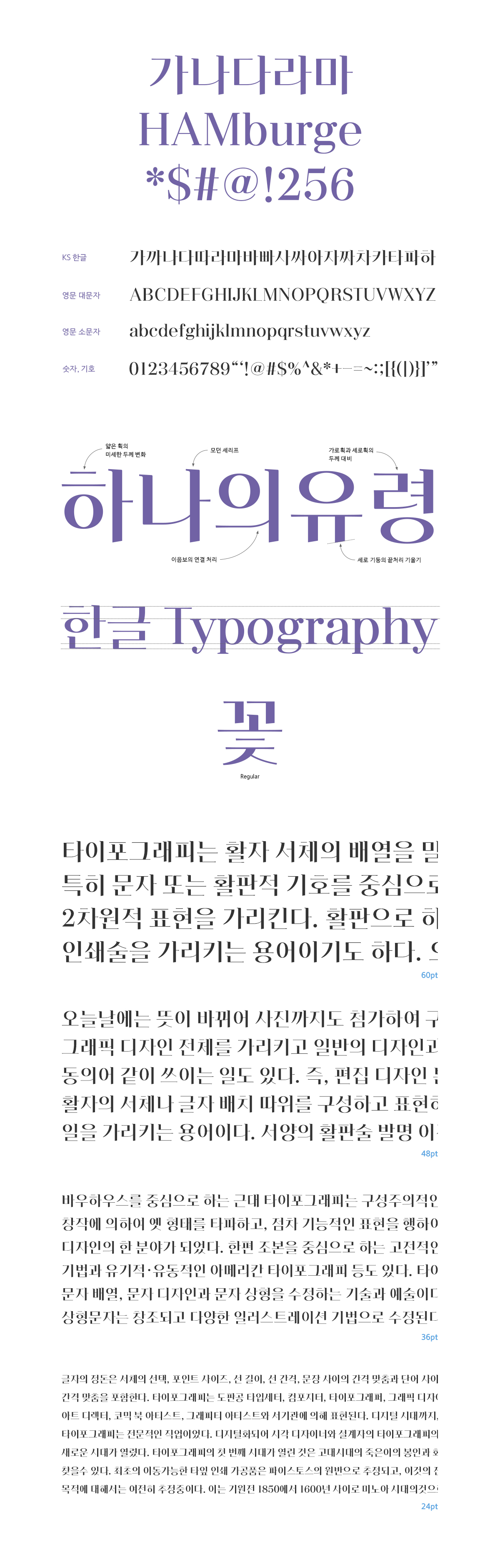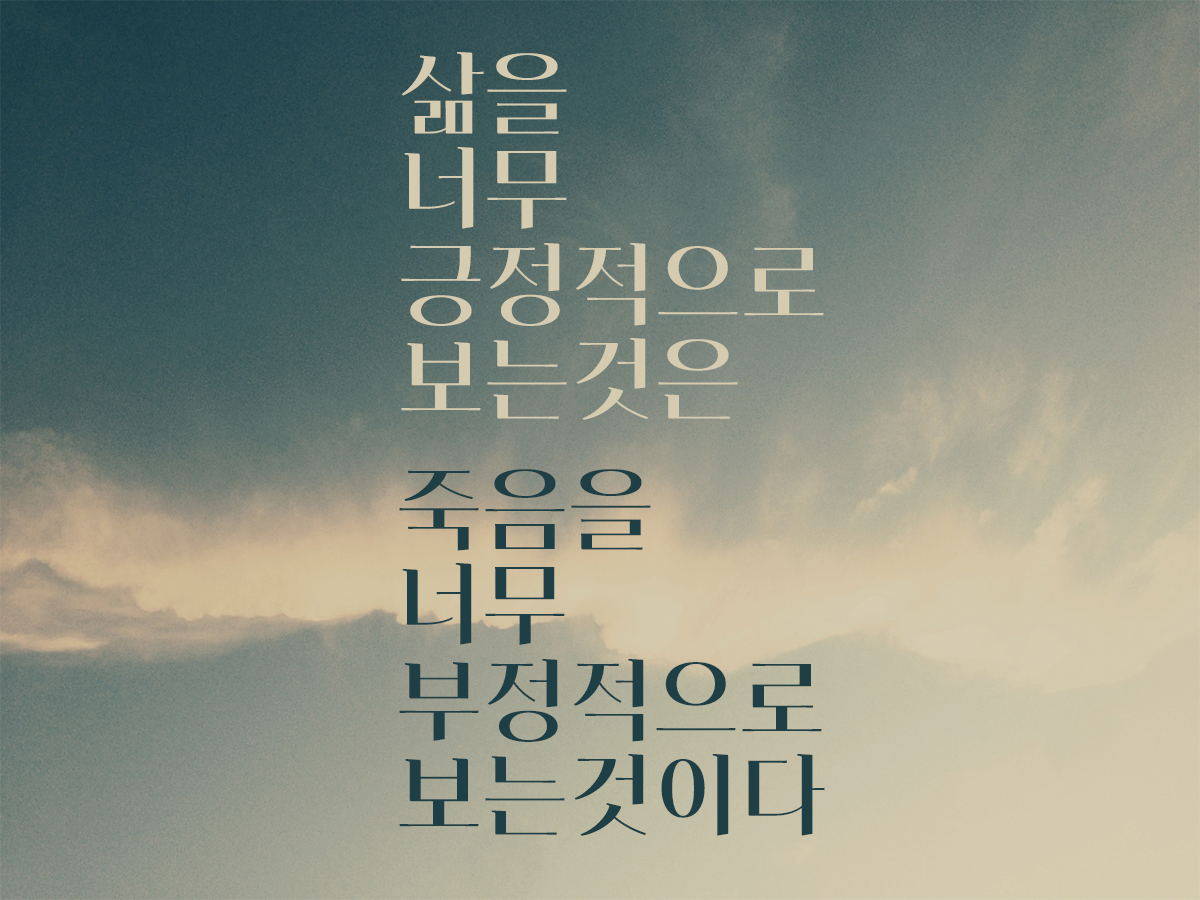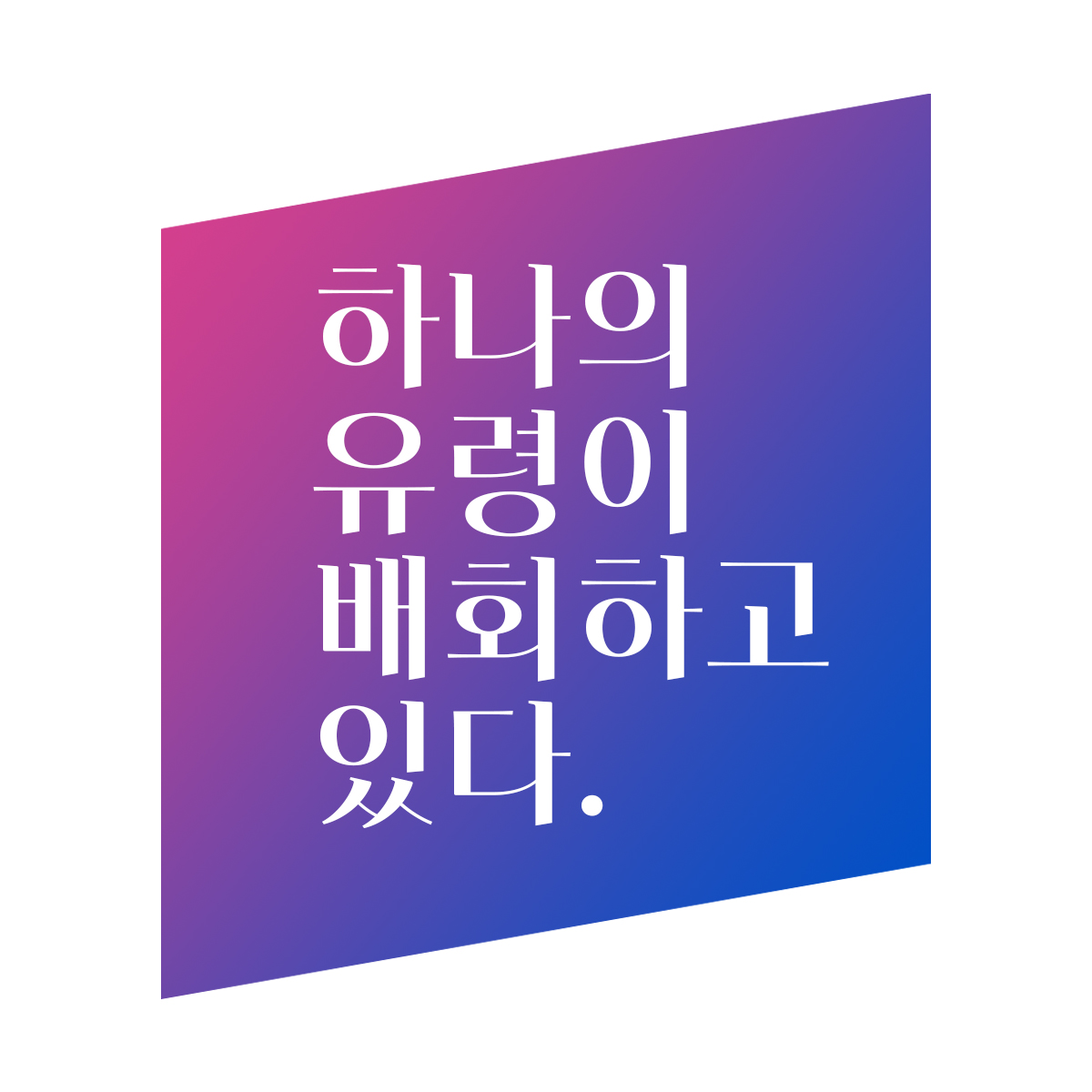
HG백야
HG백야는 획의 강한 대비가 특징인 고딕 모듈의 제목용 서체입니다. 기존의 본문형 고딕의 단단한 구조 위에서 가로획과 세로획의 두께 비율에 큰 차이를 두어 예민한 느낌이 살아있는 서체가 되었습니다. 모던한 세리프는 서체에 특징적인 형태로 보여지고 있으며, 획의 끝 처리나 연결 부분의 미세하고 디테일 한 특징이 강점입니다.
Regular 낱개 폰트이며, 2,350자의 한글 글립이 디자인되어 있습니다. 한글 글립이 같은 폭으로 디자인되어 있기 때문에 Grid를 맞춰서 쉽게 활용할 수 있습니다. 영문 디자인 또한 한글과 어울릴 수 있도록 비슷한 두께 대비를 가진 모던 세리프 서체로 디자인되었습니다.
• HG백야 / HGWhitenight